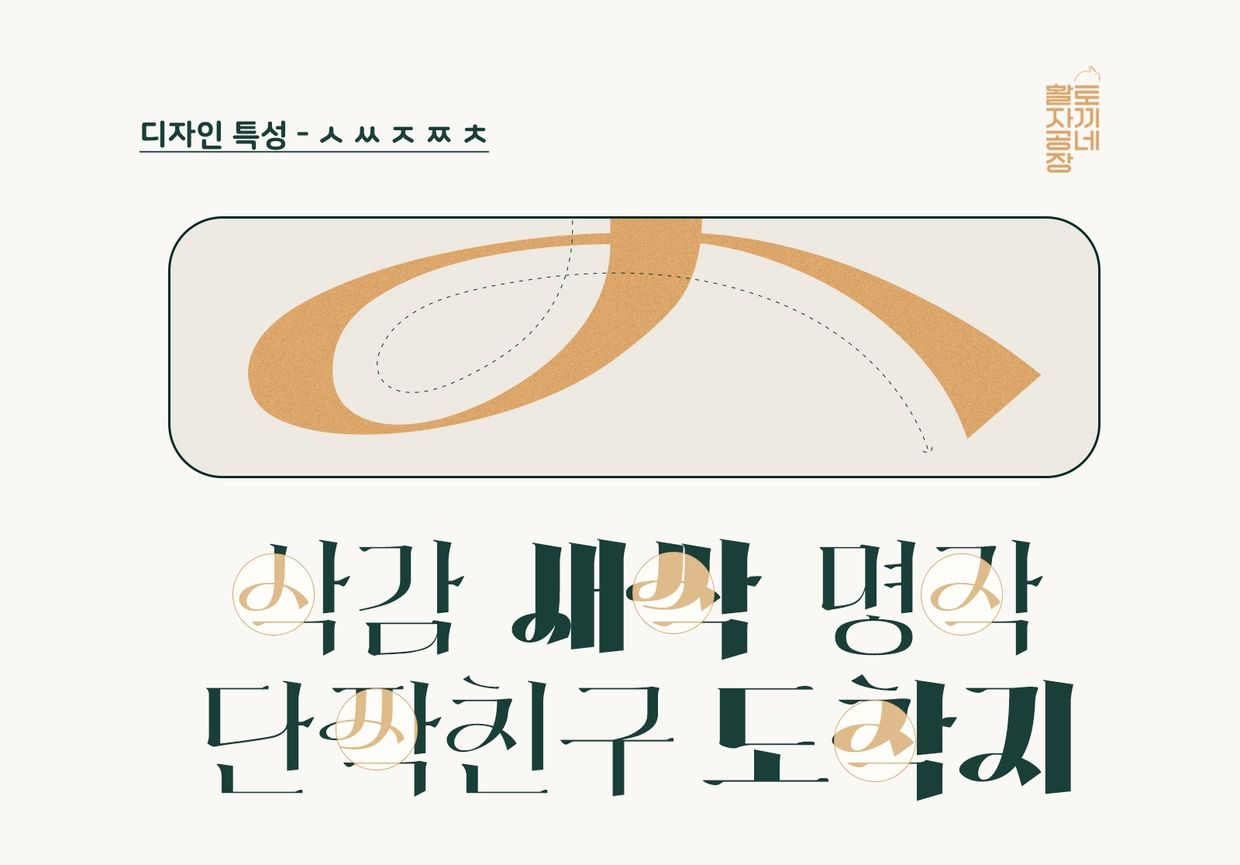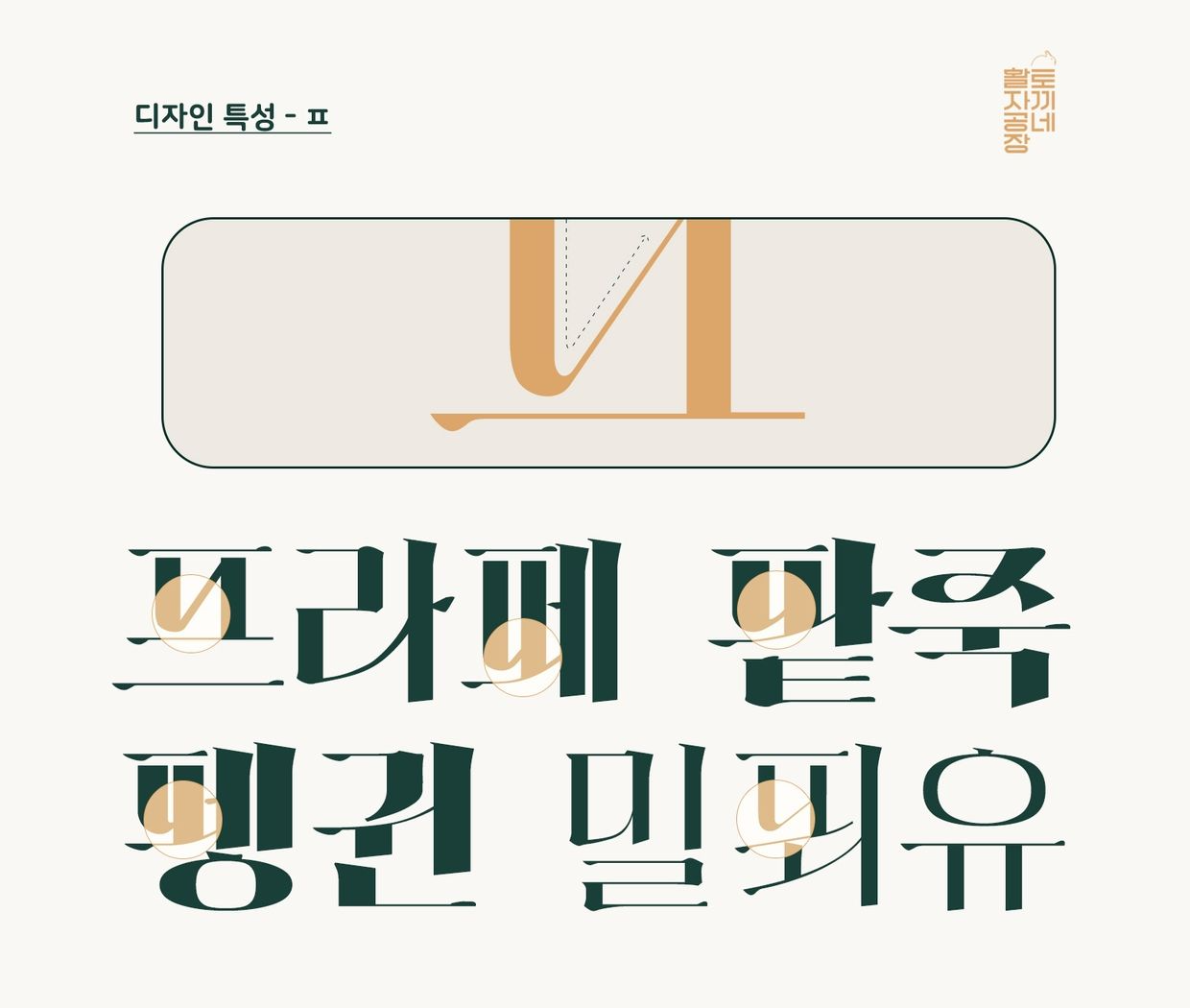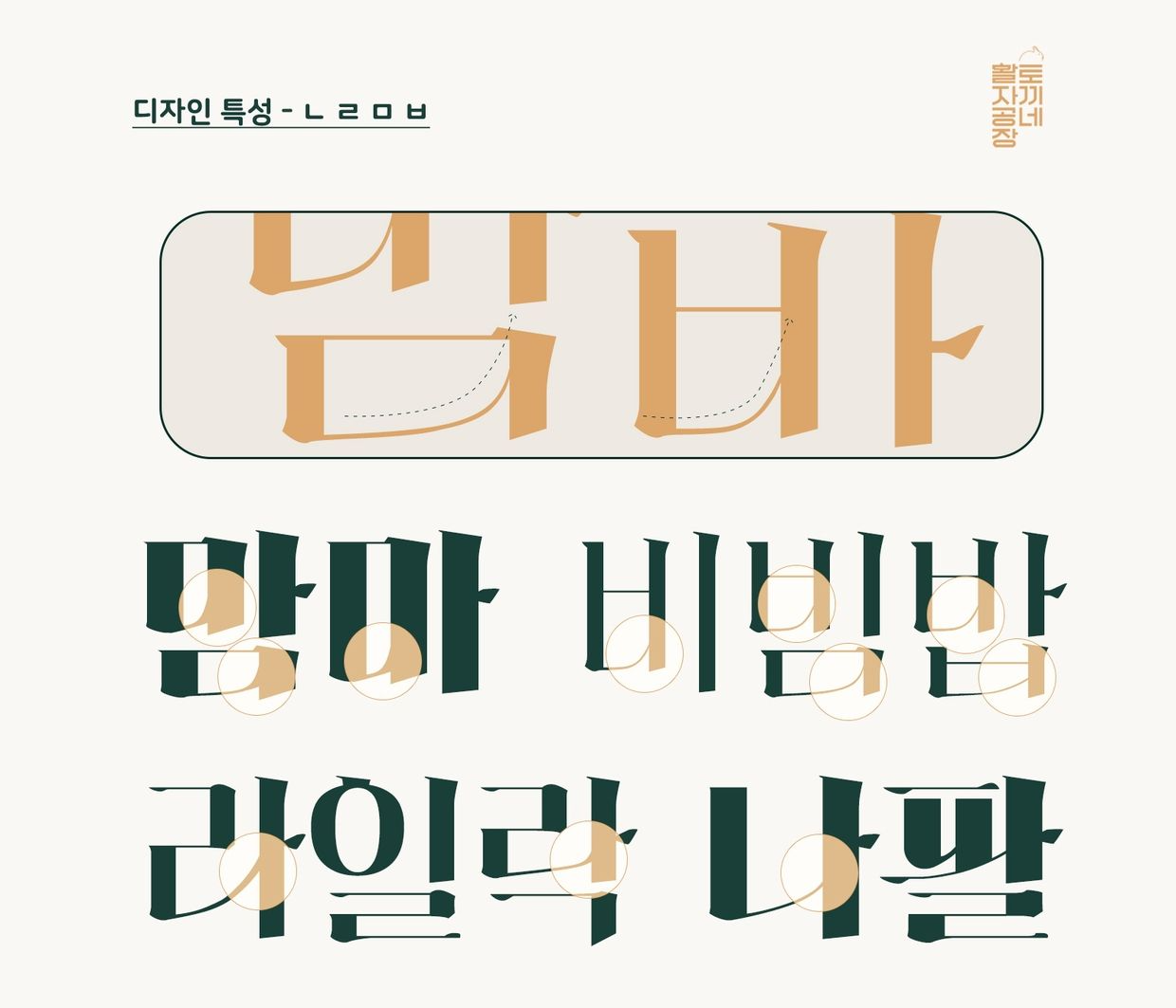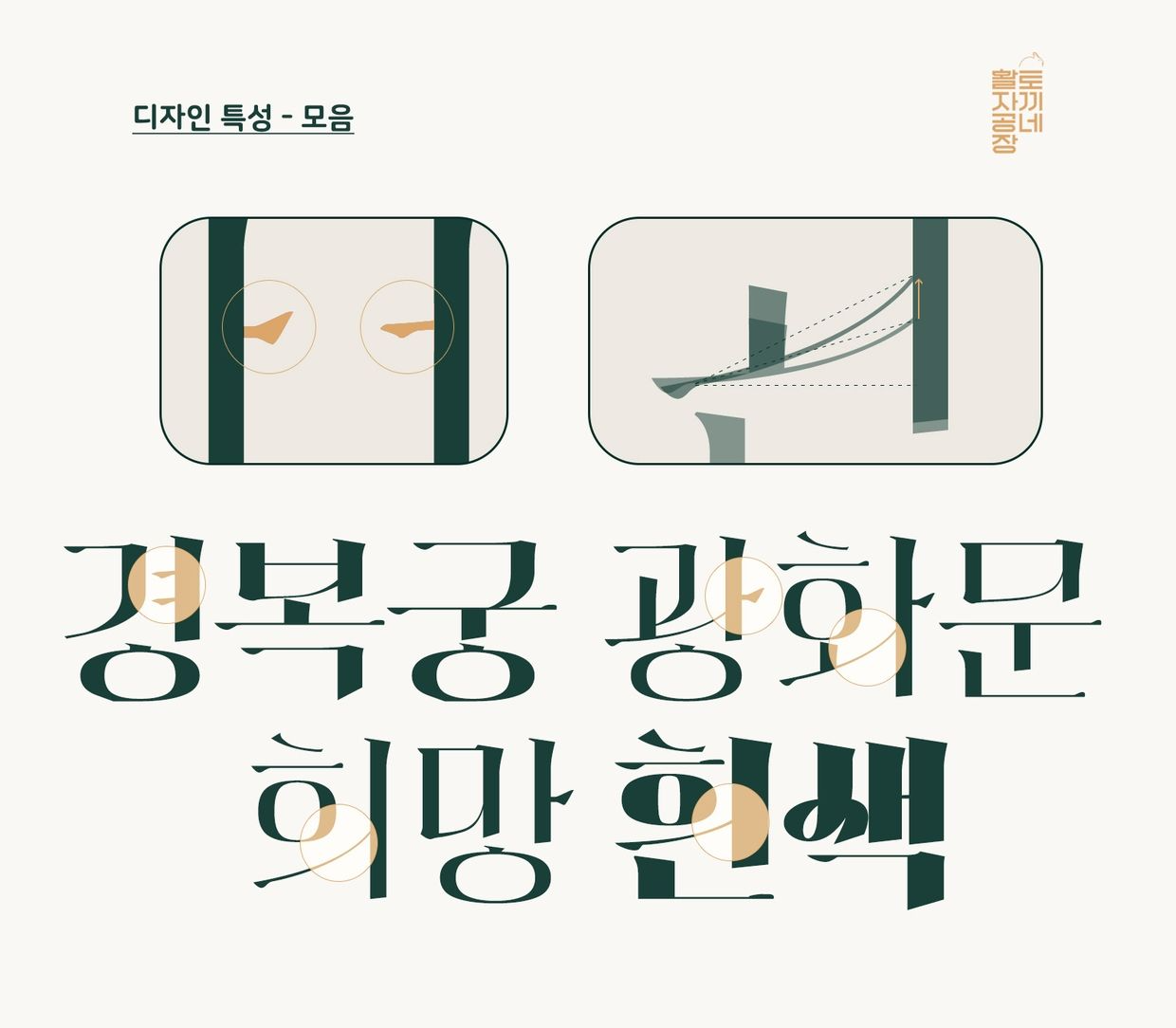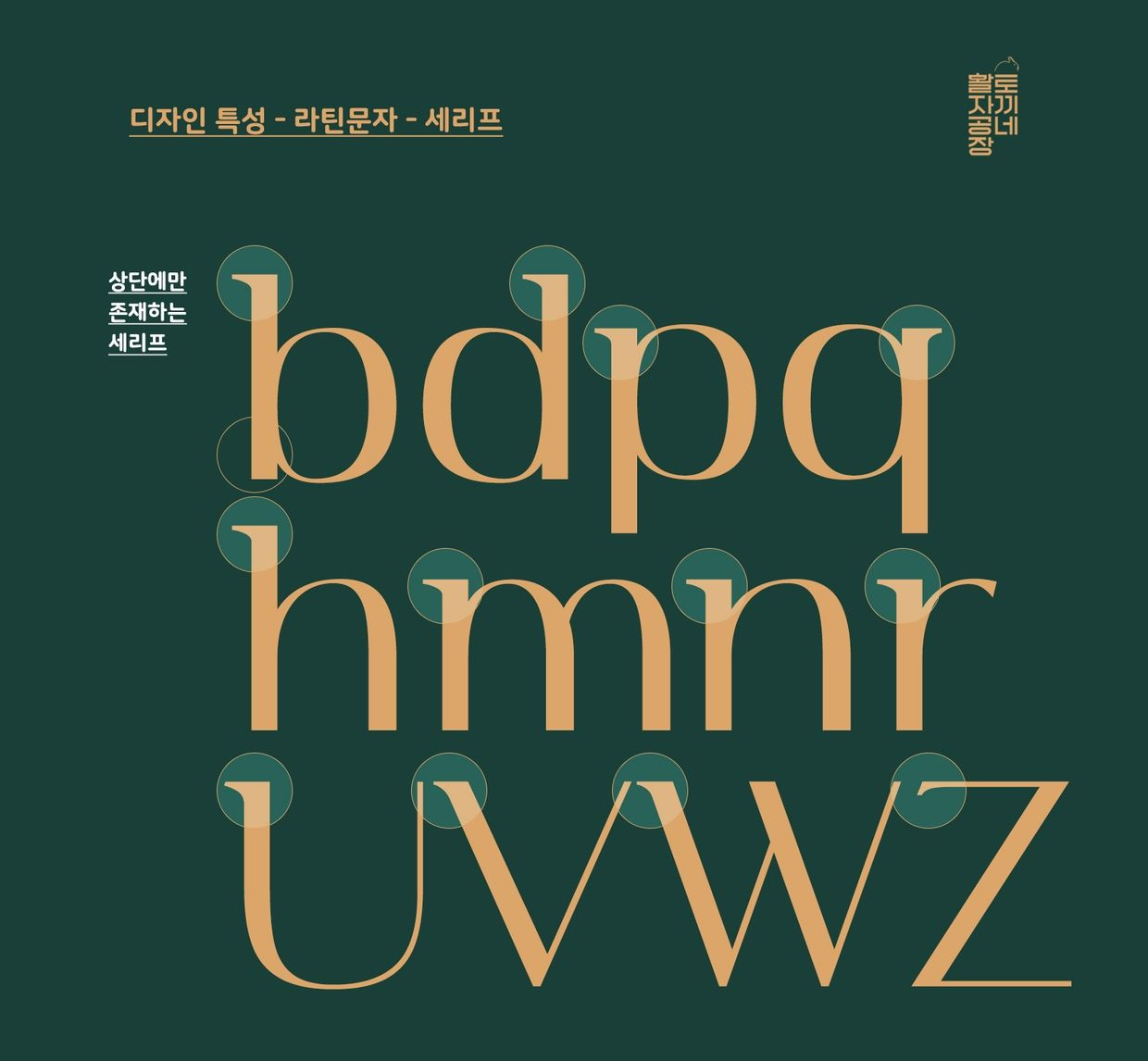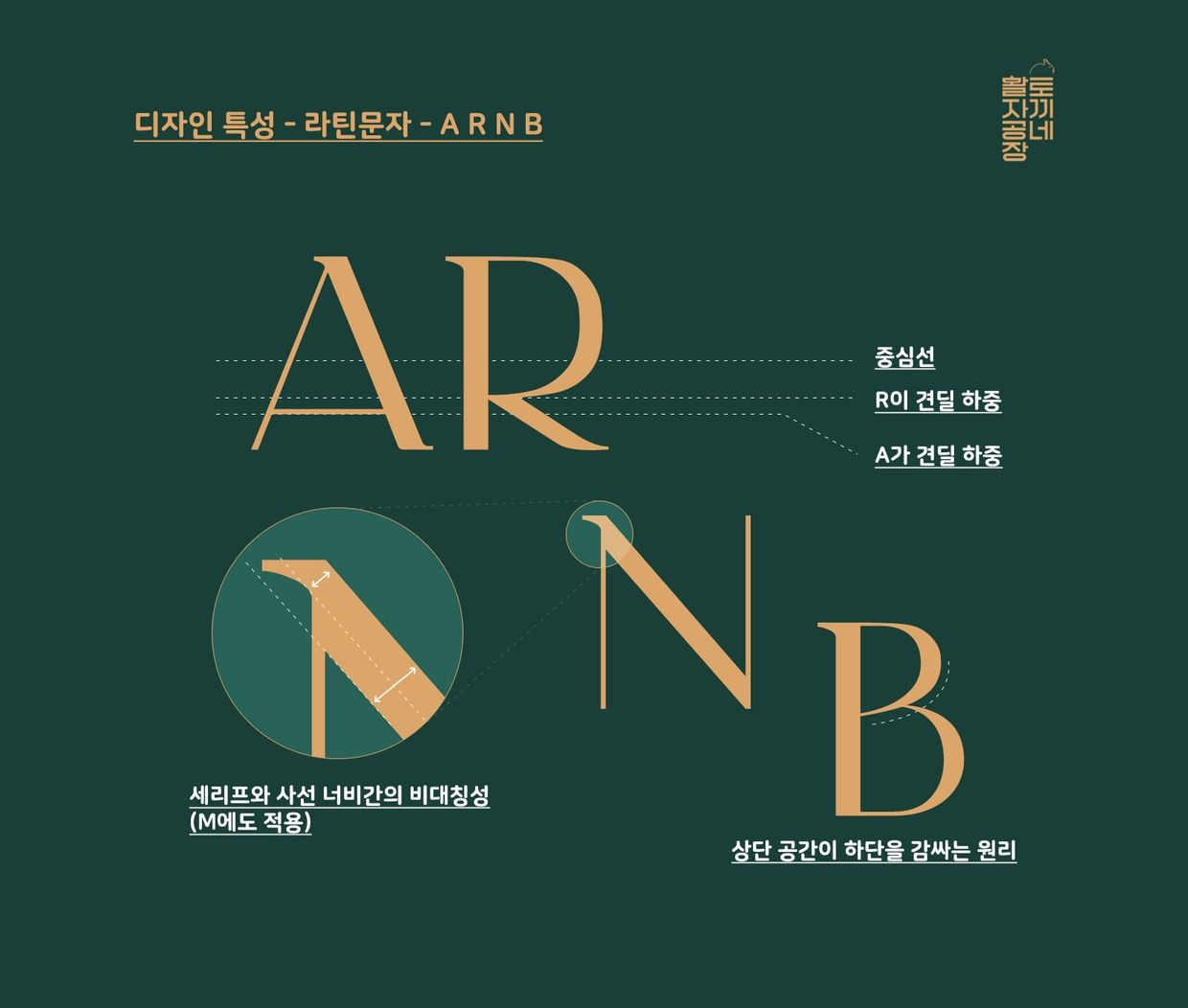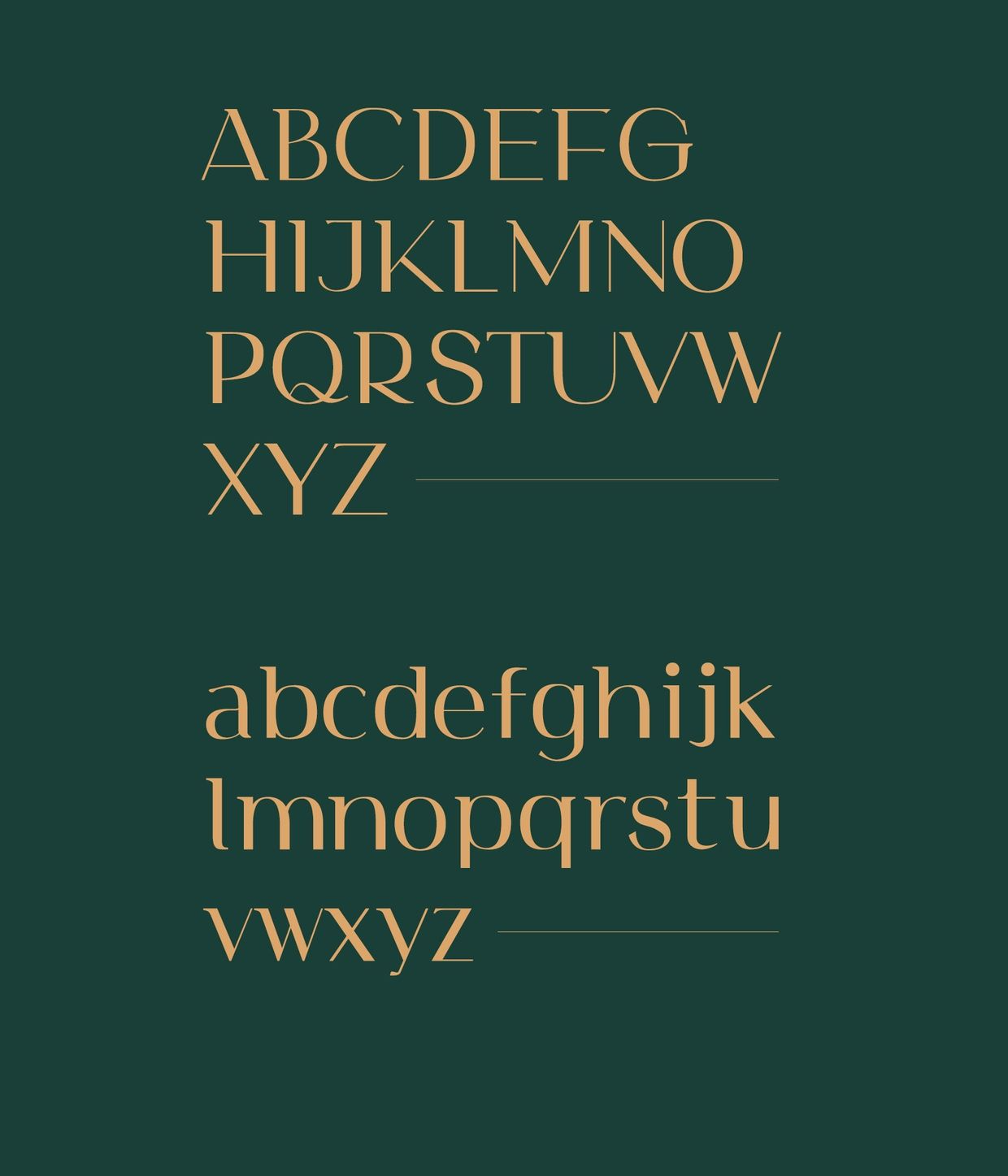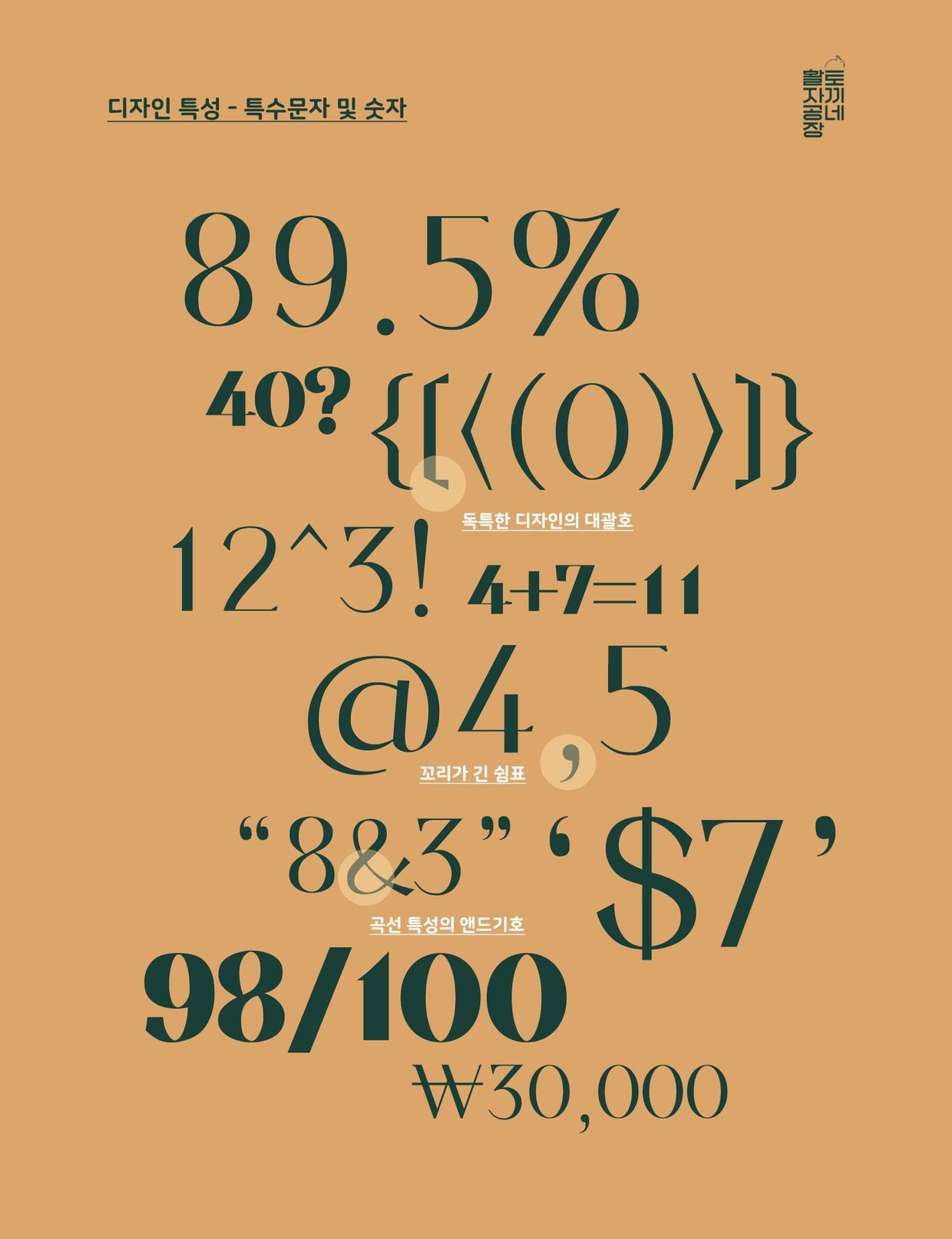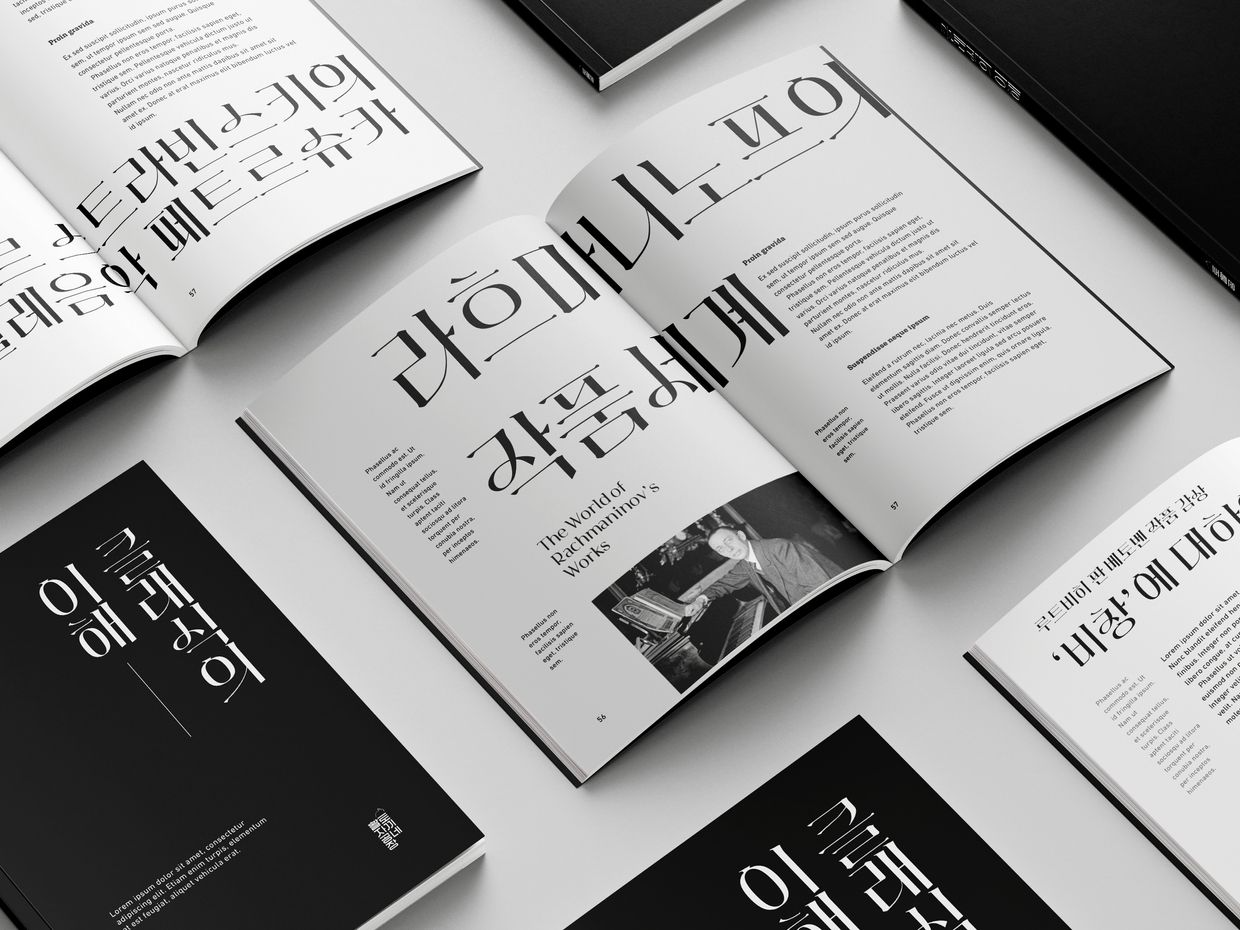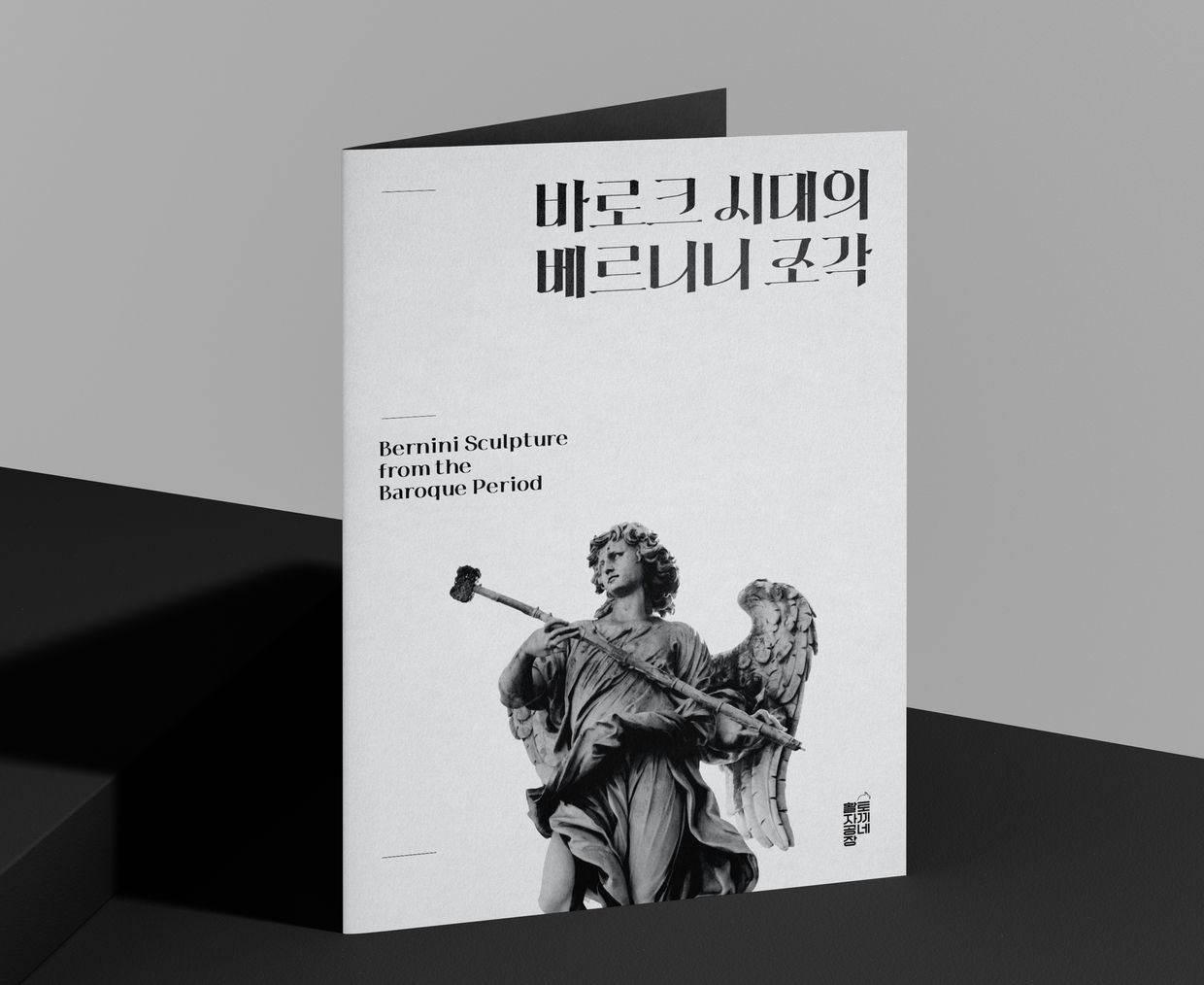
HS봄바람체는 HS계절시리즈의 첫번째 계절인 봄을 형상화한 작품으로, 여러 서체 스타일 중에서도 바탕체(명조)를 공부했던 시리즈였습니다. 많은 사람들이 사랑해준 것이 발전의 원동력이었고, 해를 거듭하며 디자인은 점차 완성형으로 나아감을 느꼈습니다. 그리고 출시 5주년이었던 2022년, 저는 HS봄바람체 4.0를 완성했습니다.